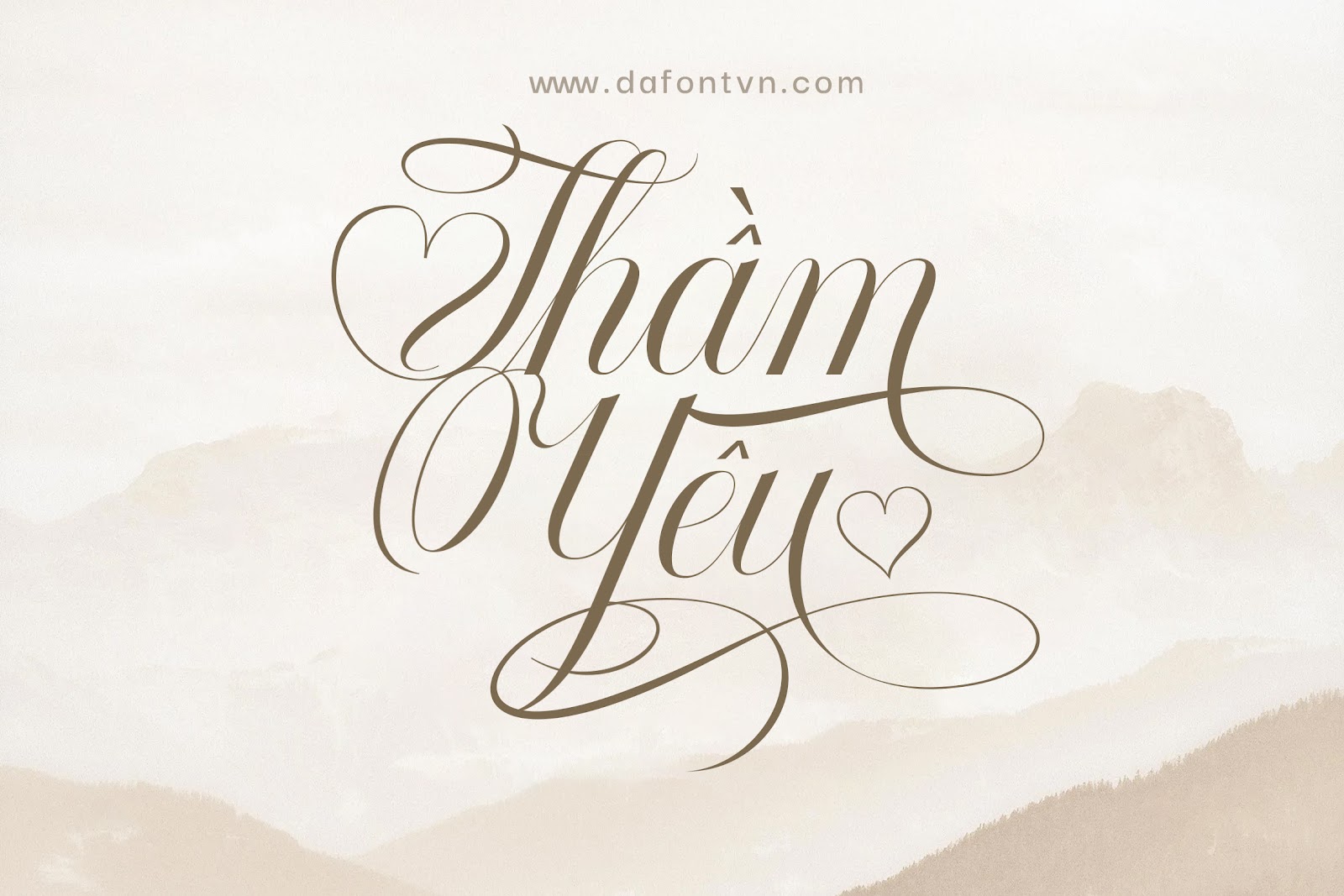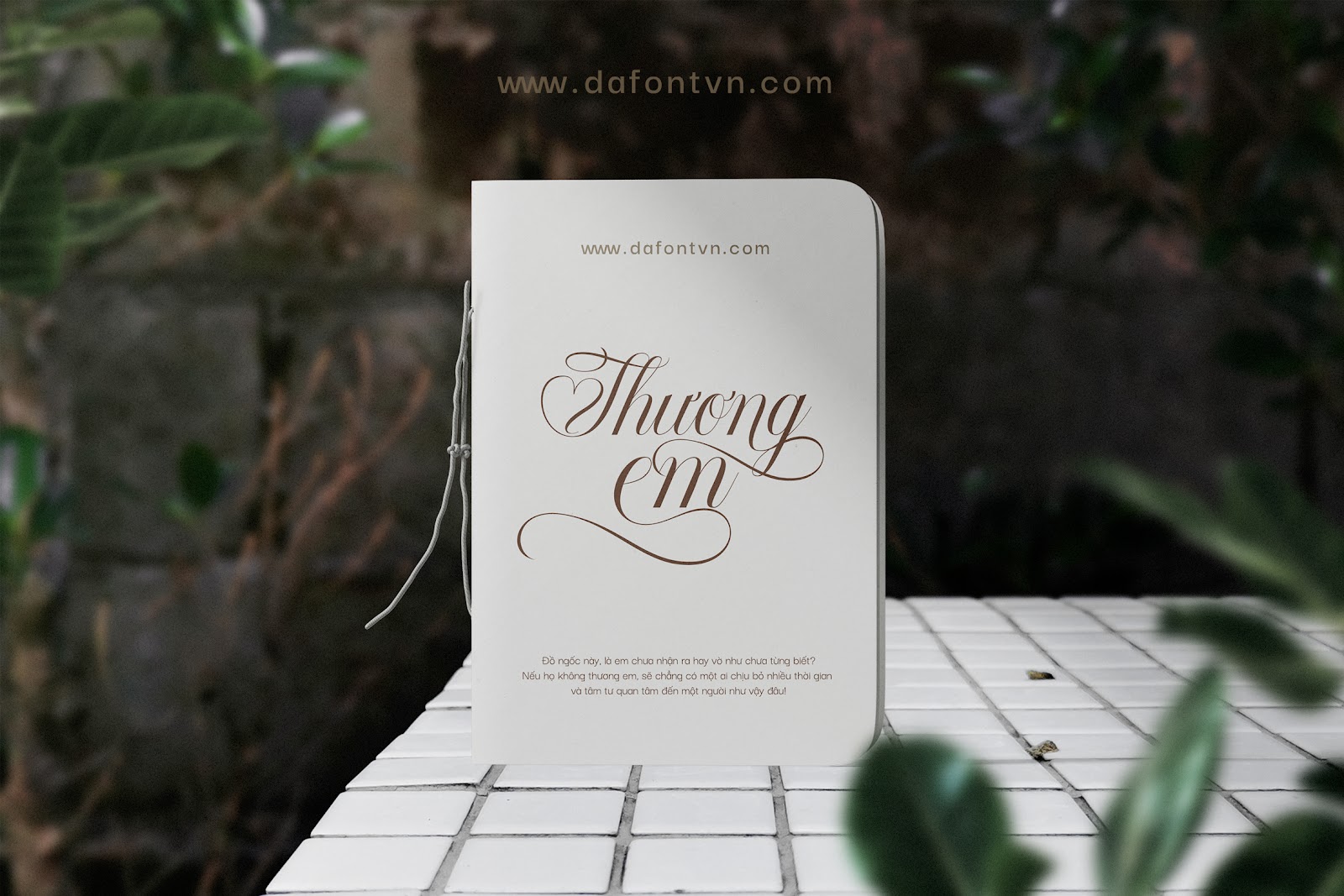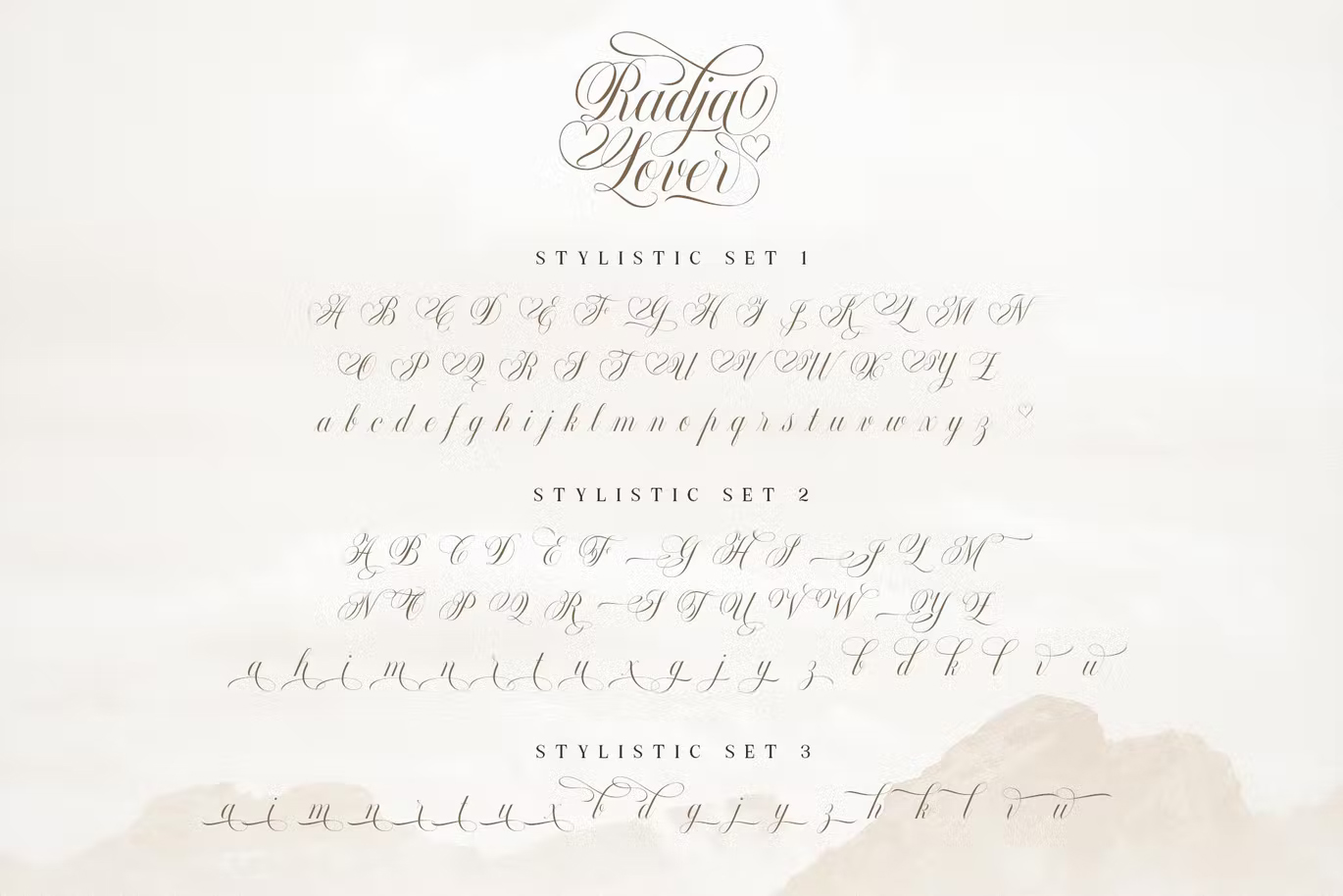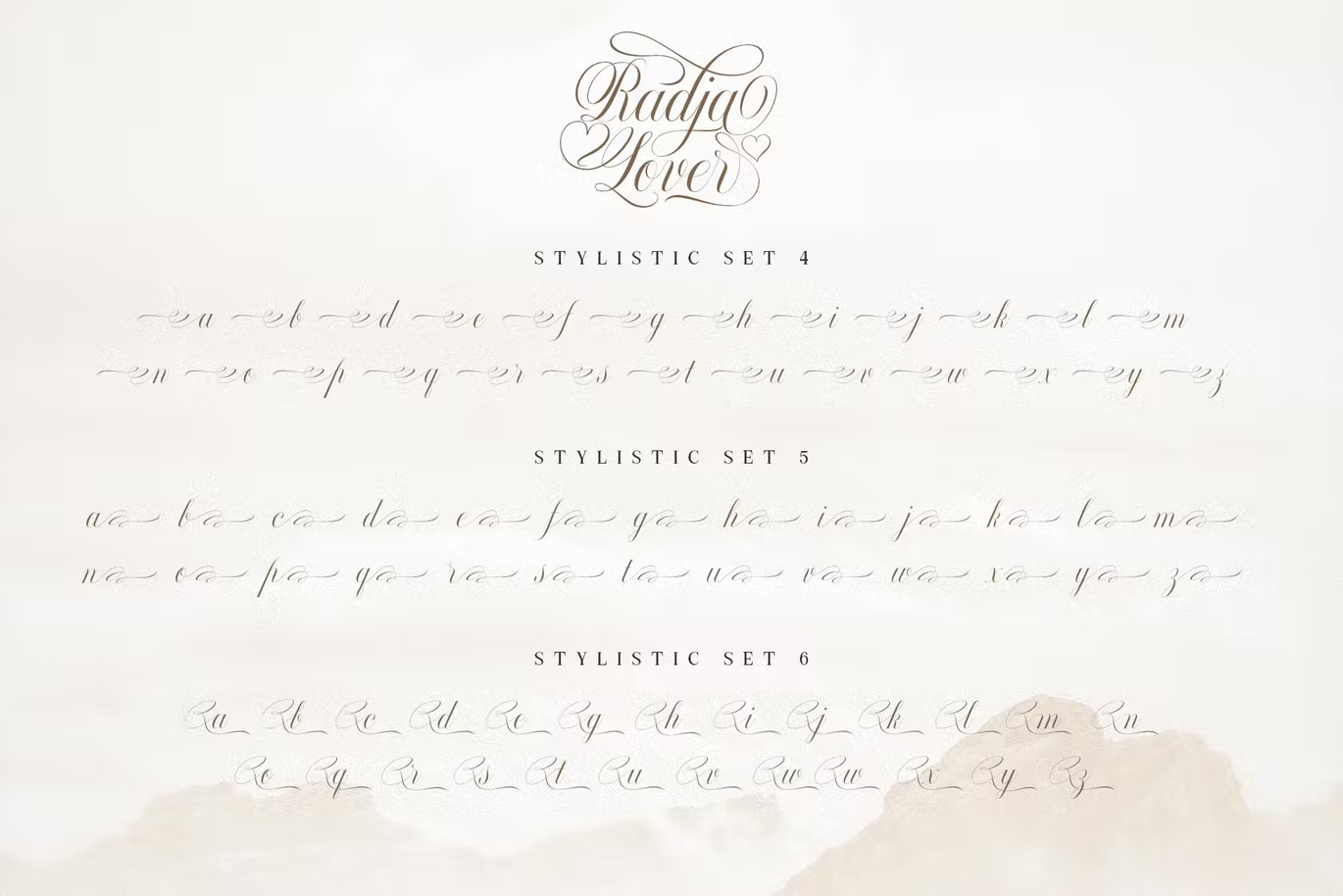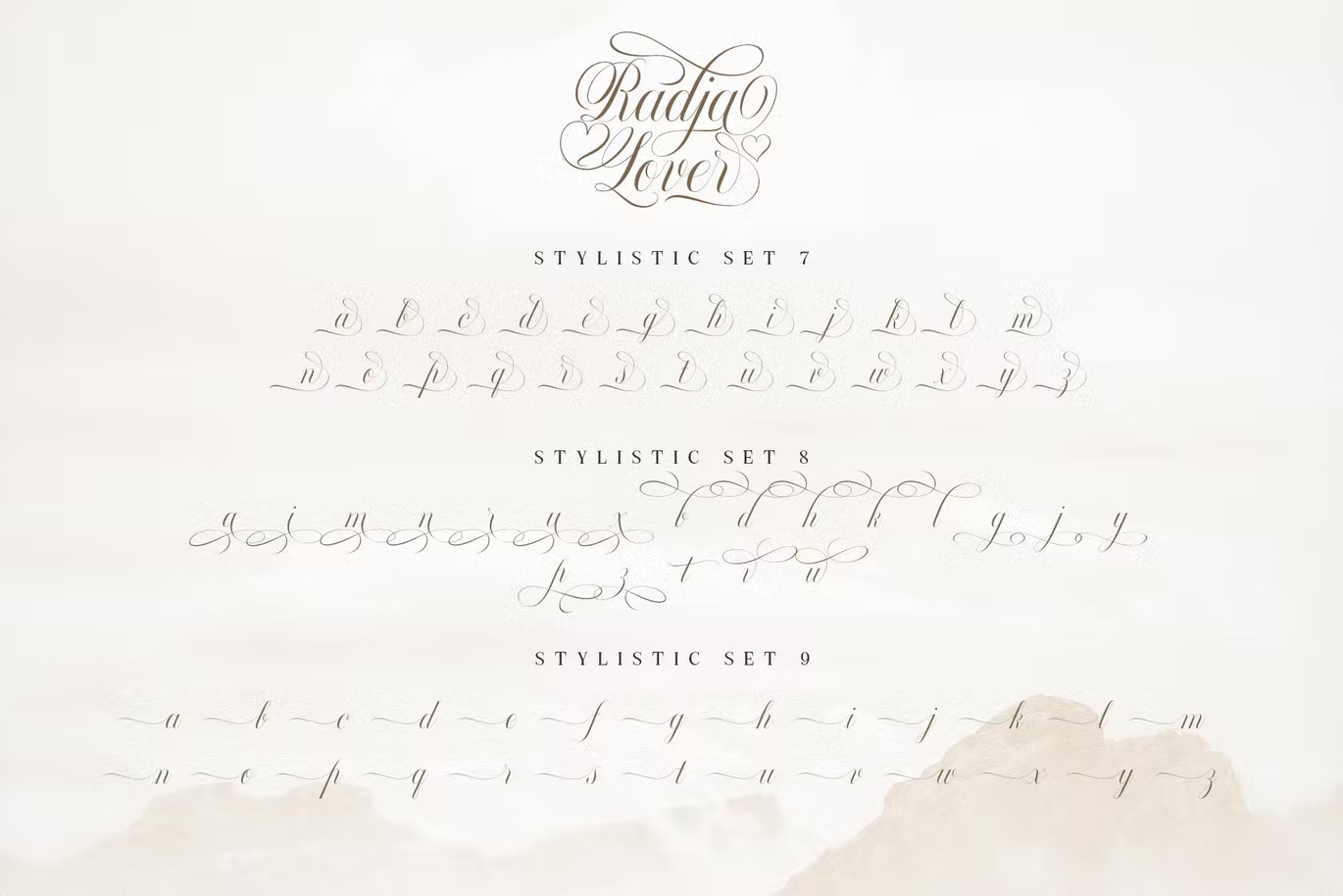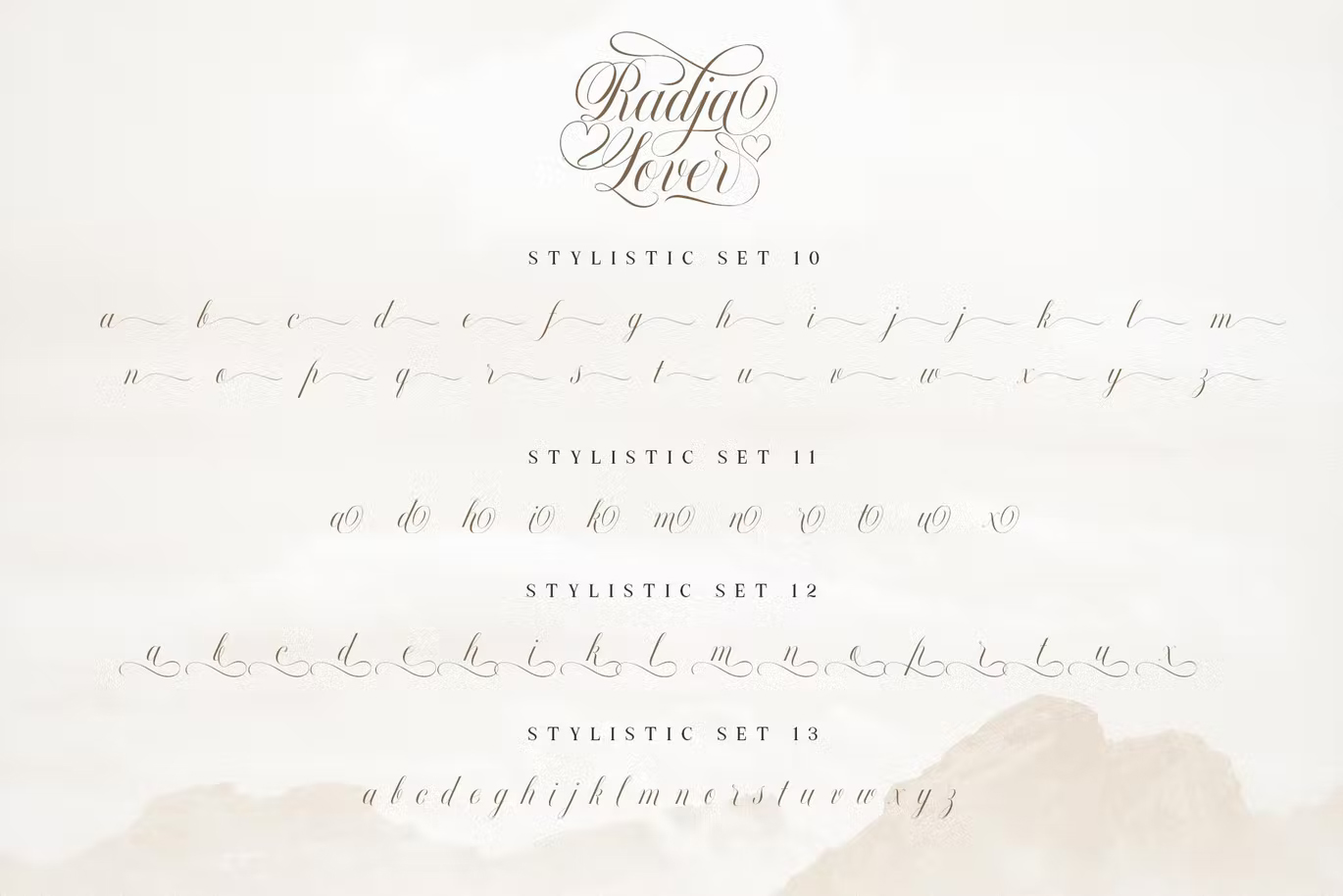
Font Radja Lover Script việt hóa siêu xinh đẹp
Radja Lover Script là phông chữ lấy cảm hứng từ ngày lễ tình nhân mang phong cách lãng mạn. Font Radja Lover Script được tuân theo phong cách script hiện đại đơn giản và ấn tượng, bên cạnh đó phông chữ này đi kèm với hơn 800 glyhp và có các glyph được tác giả thiết kế với nét hình trái tim độc đáo.
Phông chữ rất phù hợp cho các thiết kế như thiệp chúc mừng, thiết kế logo, thiệp đám cưới, typo lãng mạn… Ngoài ra, font được việt hóa đầy đủ, chỉnh sửa và tối ưu hóa lại cũng như tất cả các alternate và glyph đều được hỗ trợ bởi Unicode.
Font Radja Lover Script việt hóa
Font việt hóa Radja Lover Script
Radja Lover Script style set 1
Radja Lover Script style set 2
Radja Lover Script style set 3
Radja Lover Script style set 4